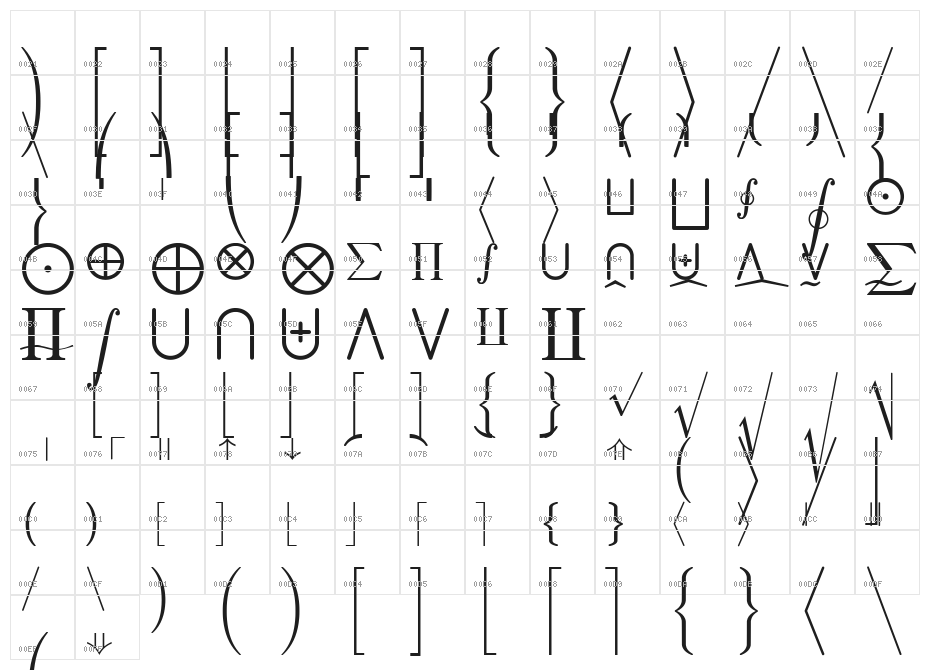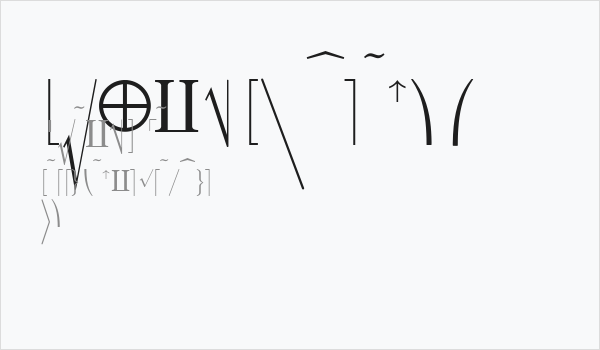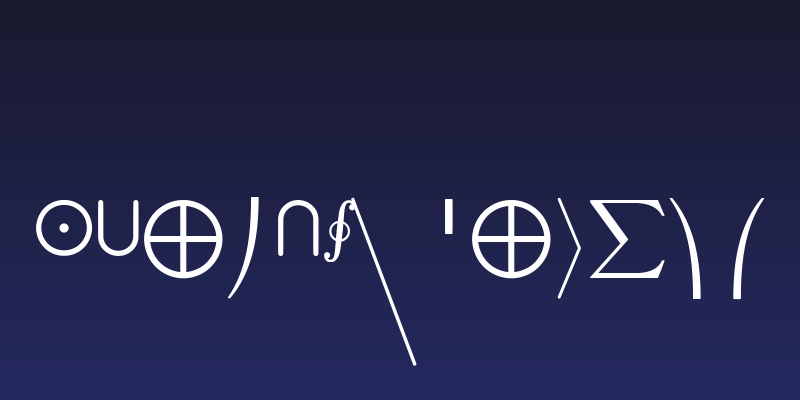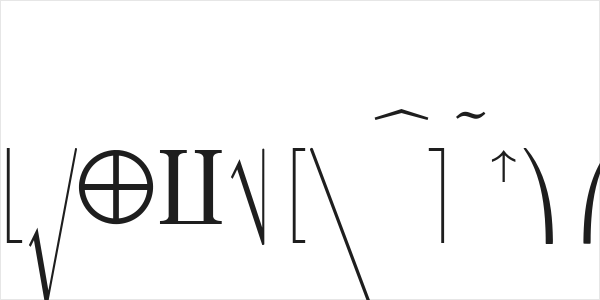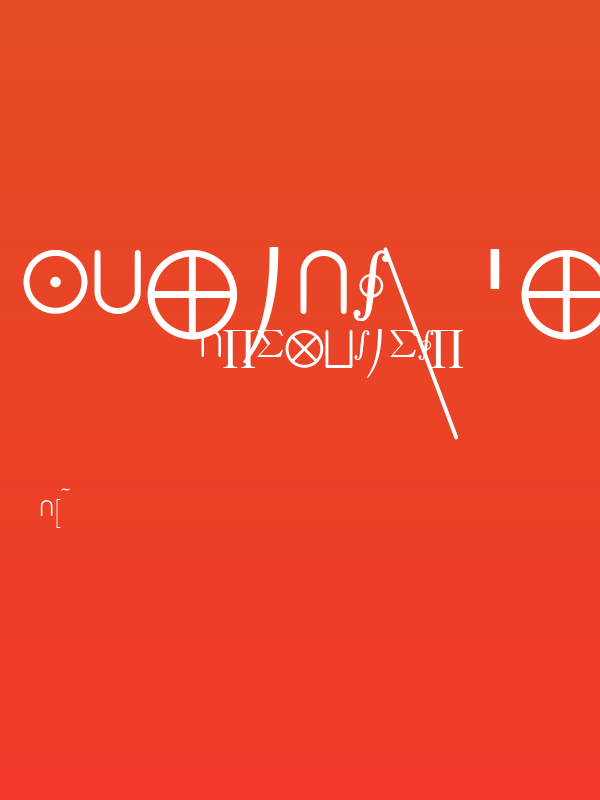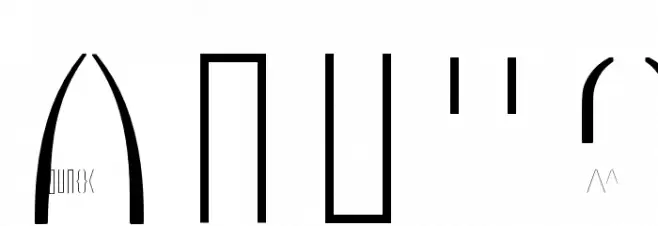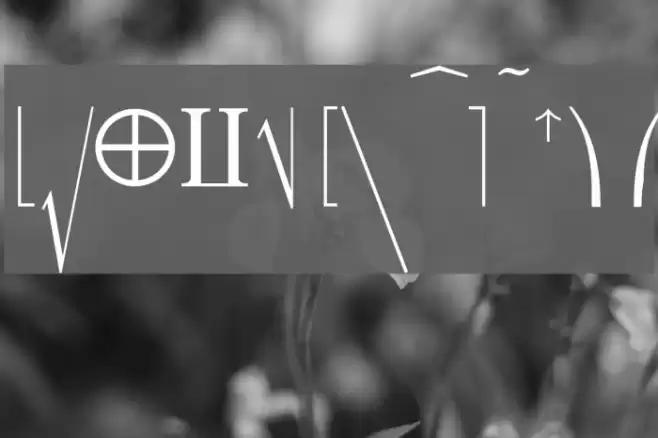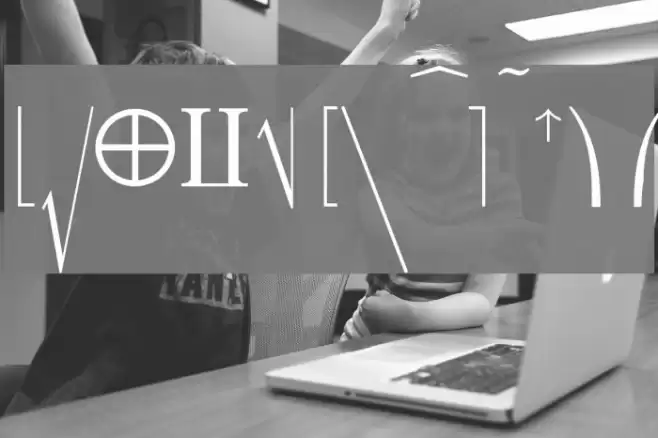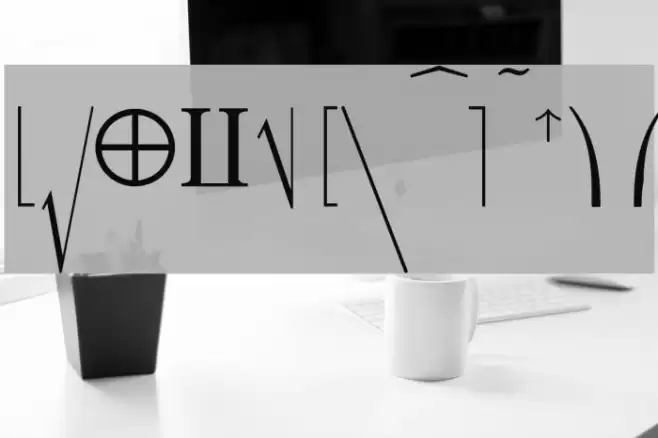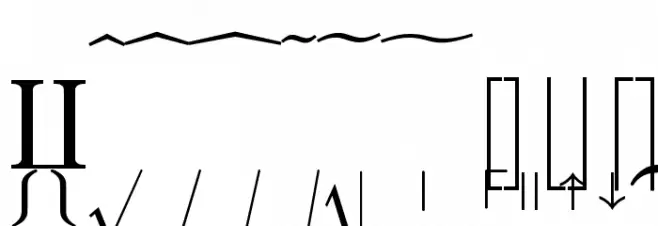
jsMath-cmex10 Font
| 全体的なスタイル | Technical |
| 用途 | Mathematical notation, academic publications. |
| おすすめプロジェクト | Ideal for academic papers, scientific journals, and educational materials requiring precise mathematical notation. |